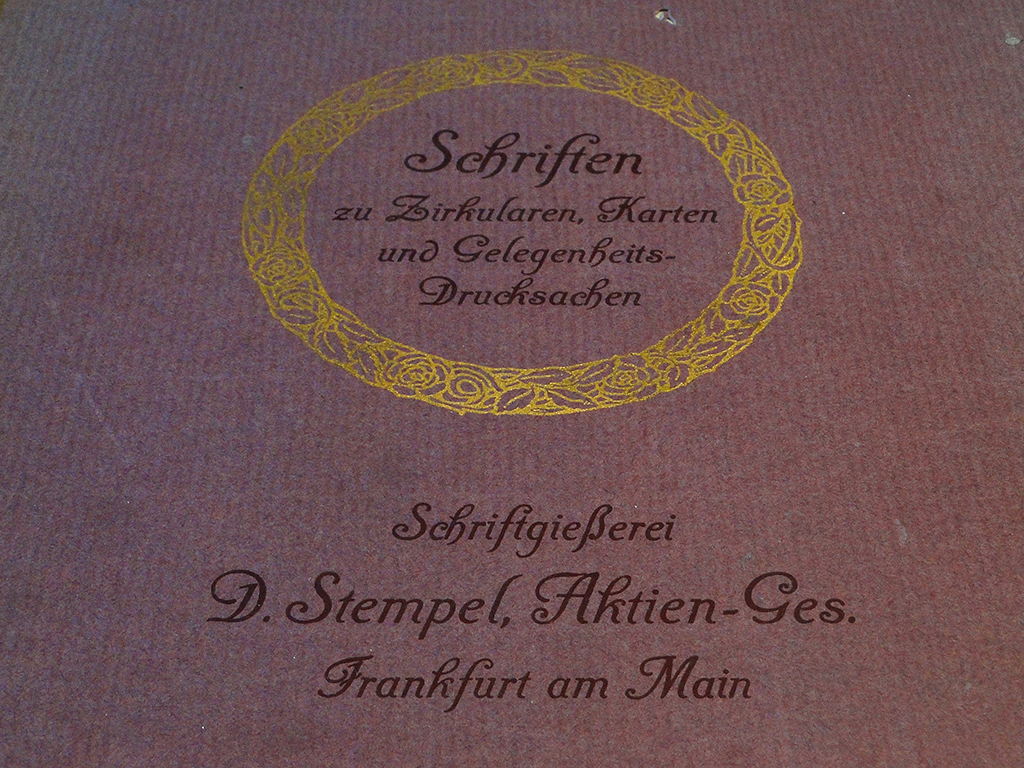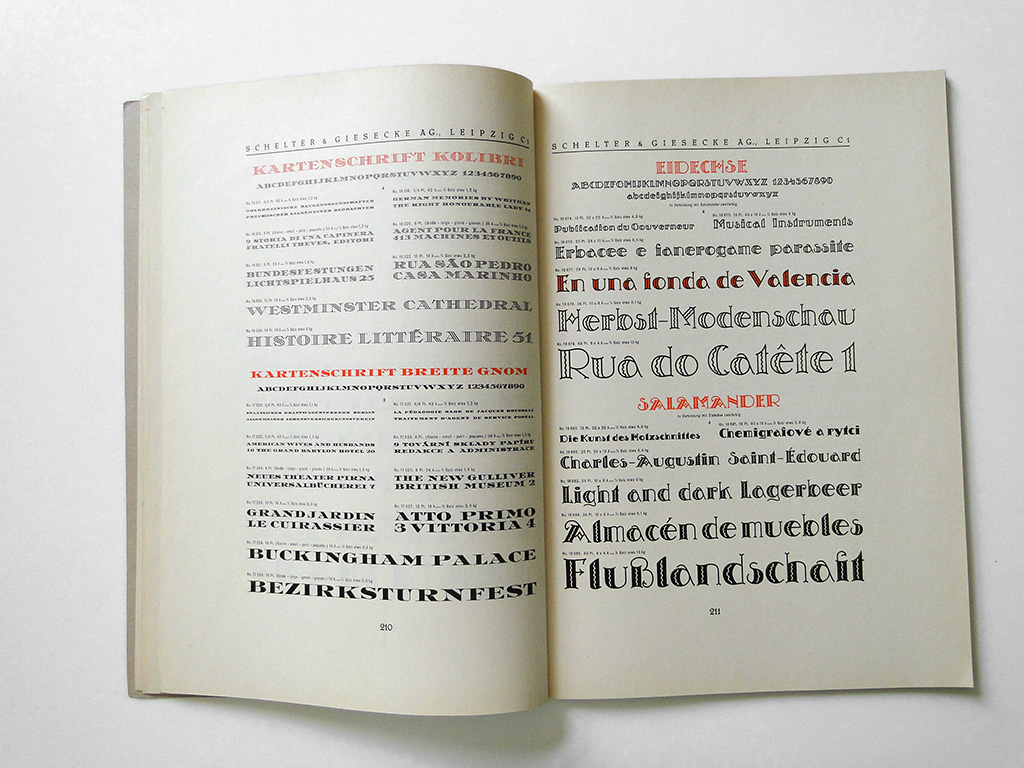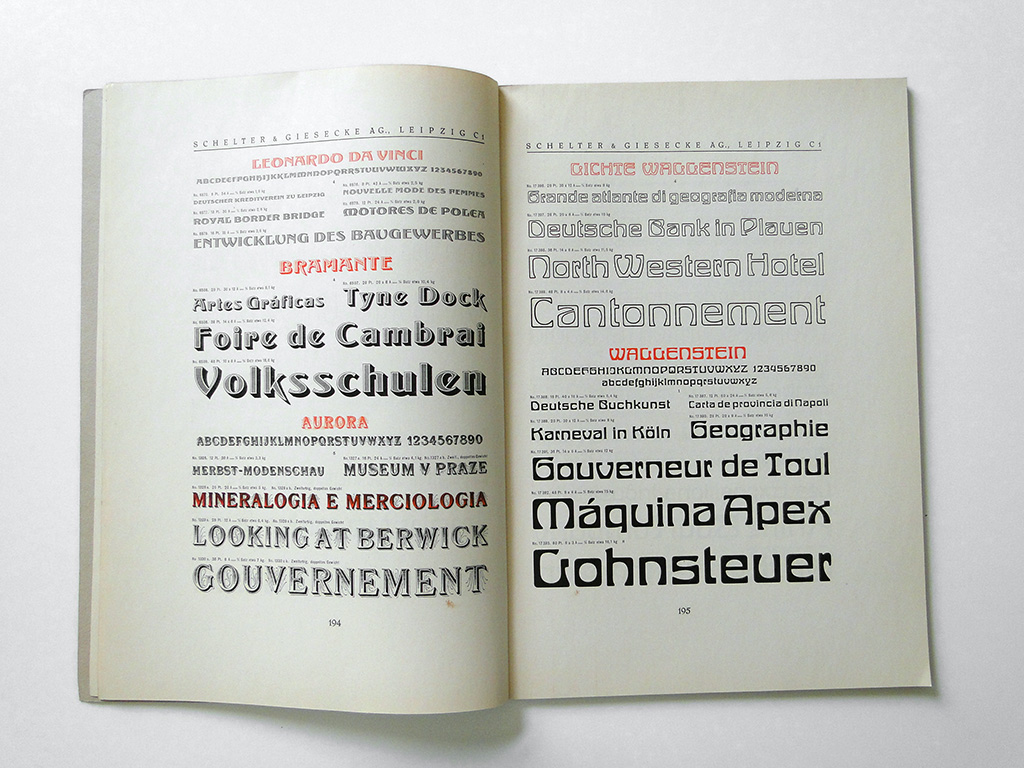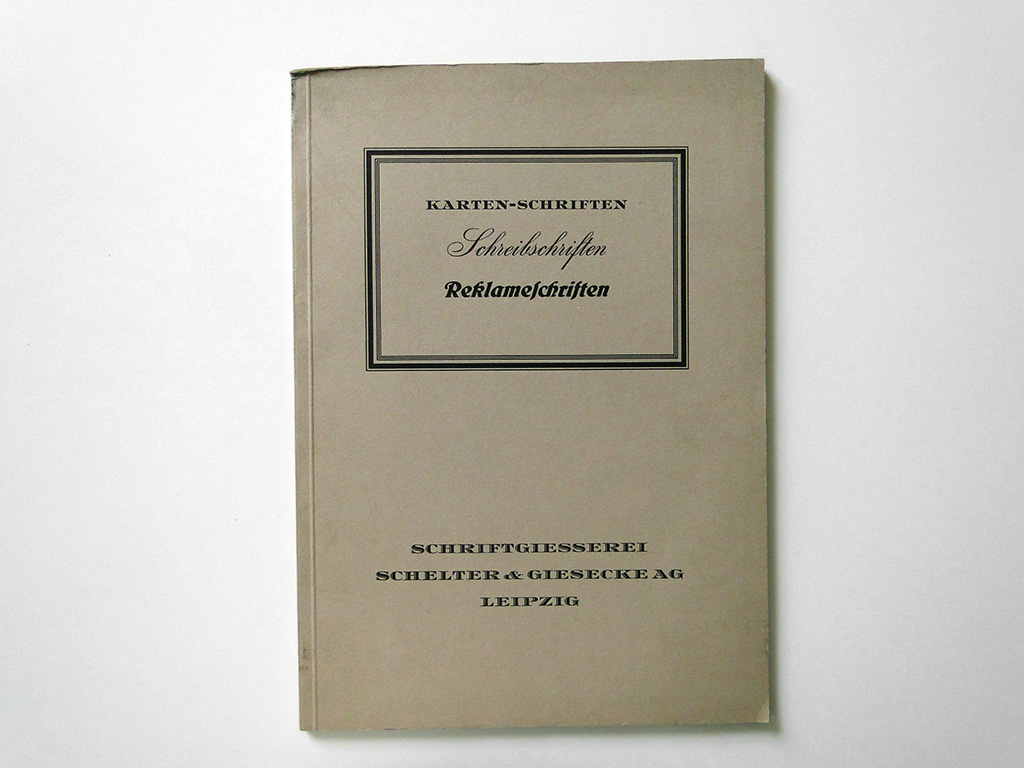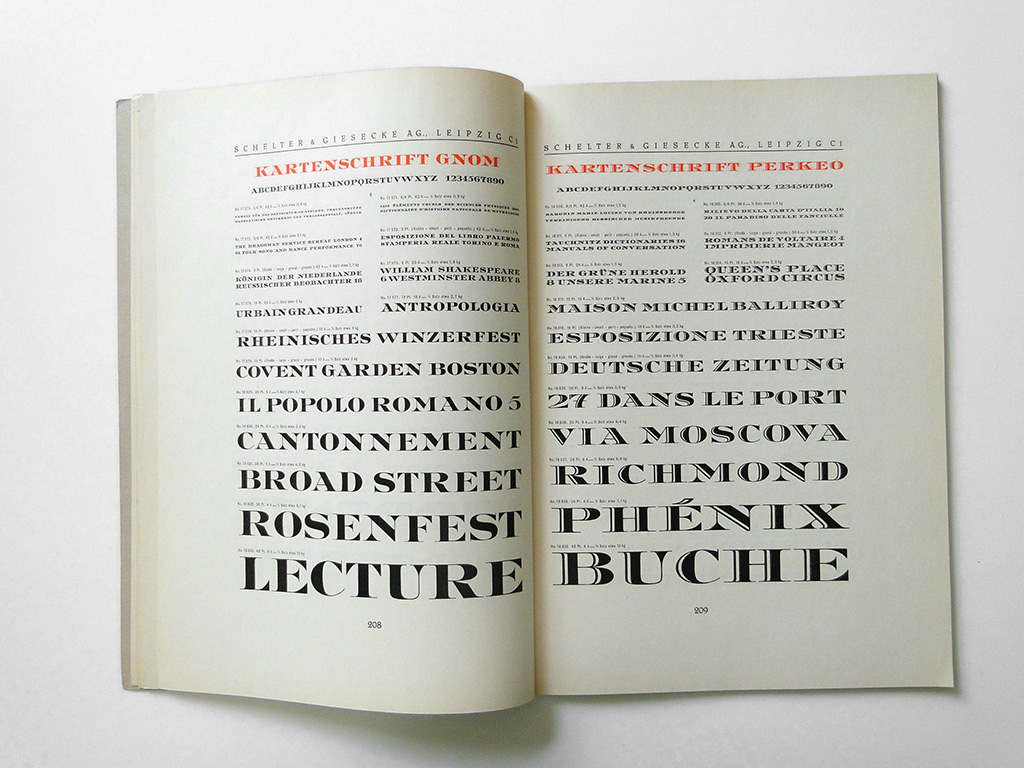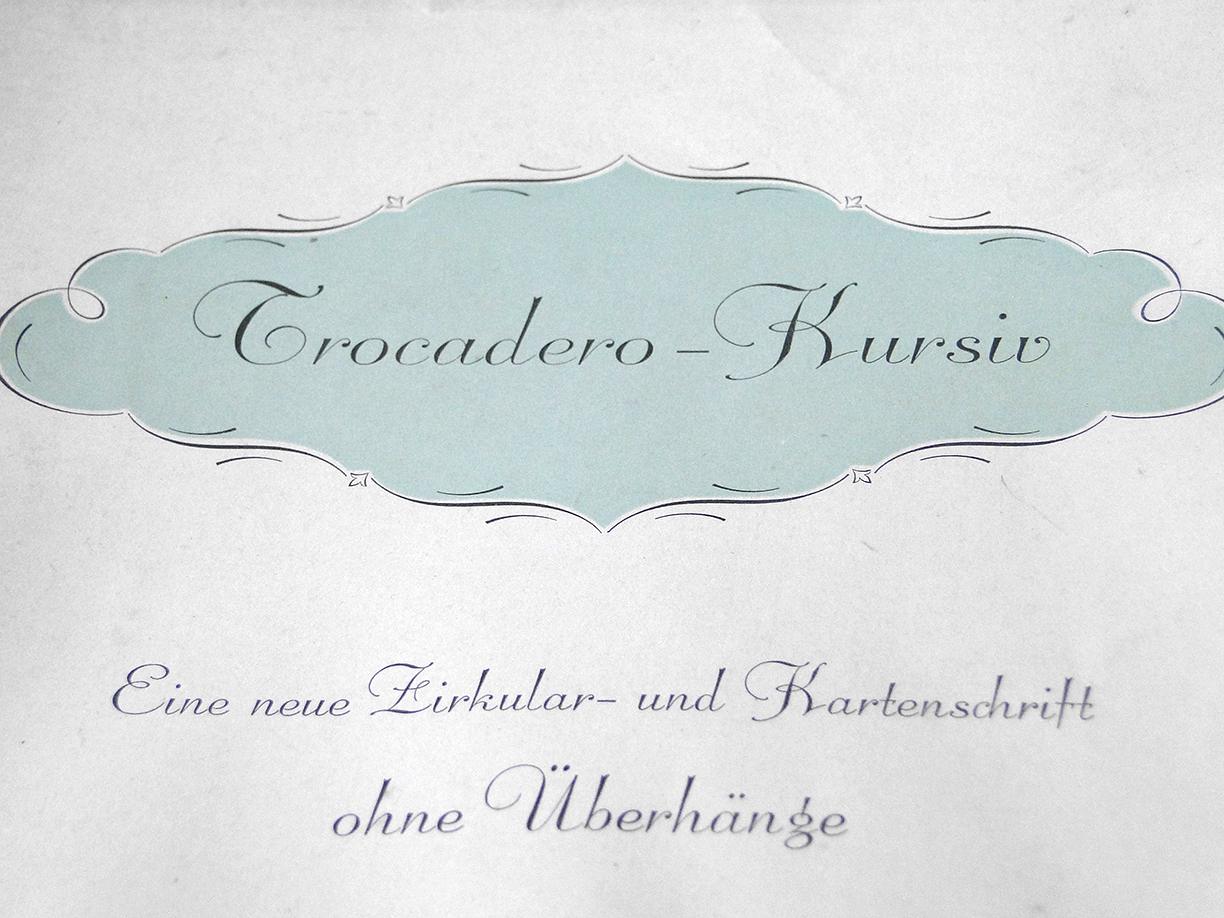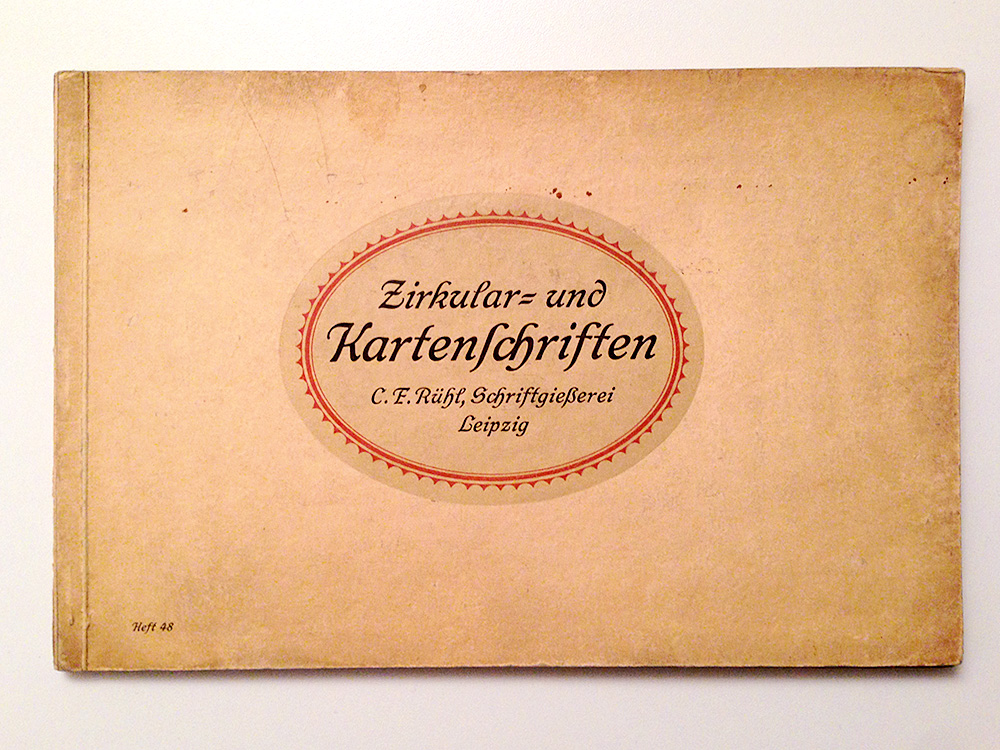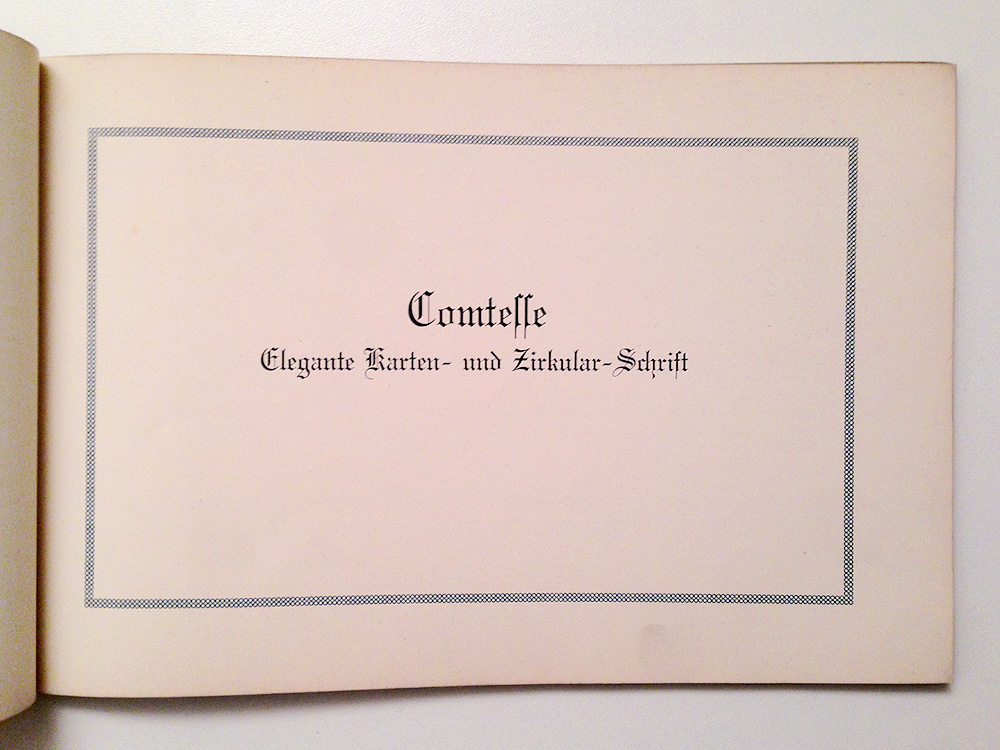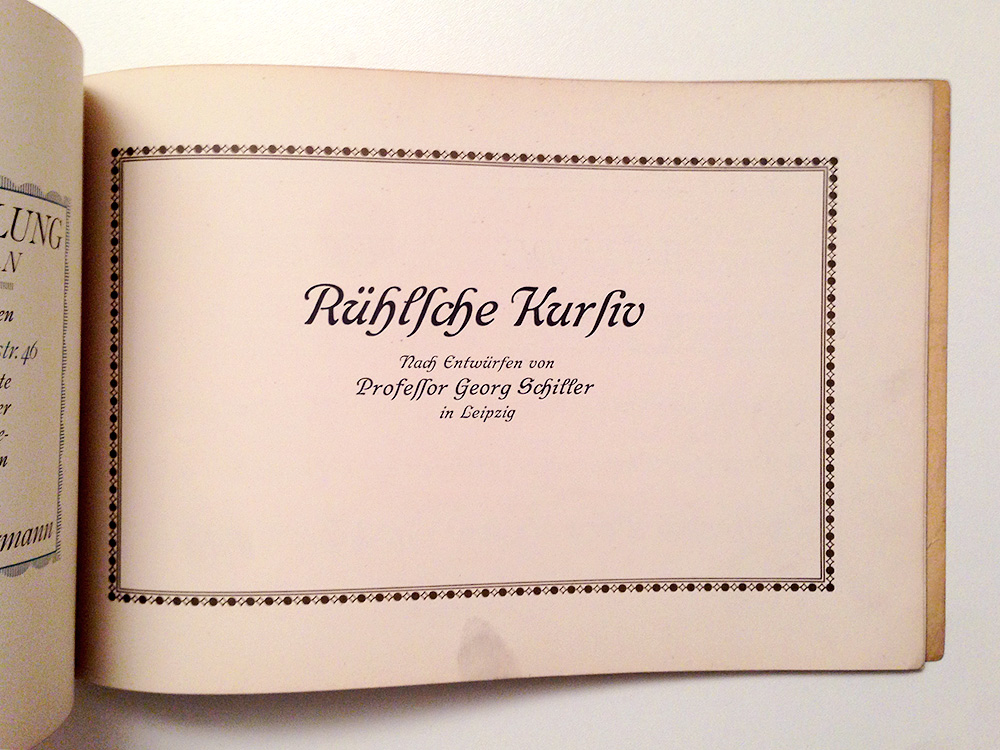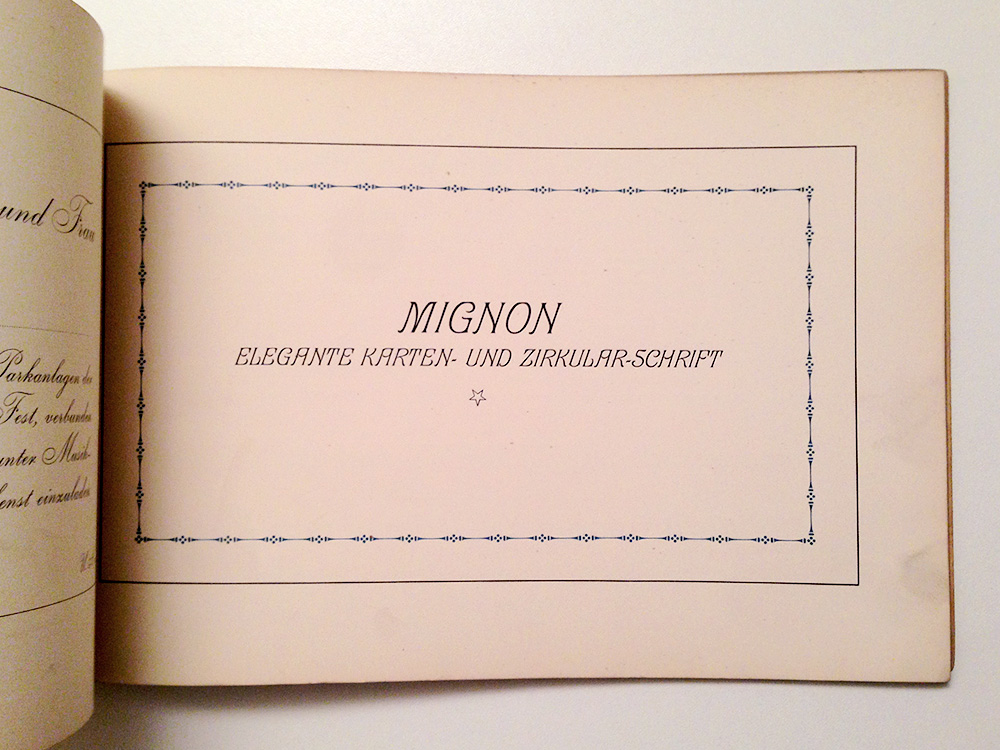
Definition Kartenschriften
Manche Bleisatzschriften werden als Kartenschriften kategorisiert oder tragen diese Bezeichnung sogar im Namen. Ich denke da immer zuerst an Landkarten, aber scheinbar bezog sich das ja früher eher auf Visitenkarten, Postkarten (?) und ähnliches.
Wie würde man »Kartenschriften« also definieren? Gibt es vielleicht sogar eine Quelle aus älterer Literatur dazu? Und was unterscheidet Kartenschriften dann vom Überbegriff(?) Akzidenzschriften?
Ich hab ein paar Muster mit Kartenschriften und kann mal schauen ob sich darin Informationen finden ...
Ohne mich jetzt auf Quellen zu berufen:
Kartenschriften weisen meist einen Kupferstich- bzw. Lithografie-Charakter auf. Dazu gehörten u. a. schraffierte Schriften, Schriften im klassizistischen Stil, Kanzlei-Gotisch, Schriften mit oft ausgeprägten Serifen und ähnliche Schriften. Diese gab es jeweils auch oft in schraffiertem Stil.
Nach Erfindung des Kupferstiches bzw. der Lithografie wurden alle möglichen Karten in diesen Druckverfahren hergestellt.
Mit den entsprechenden Schriften griff man nun im Bleisatz auf diesen Stil zurück um ähnliche Ergebnisse im Hochdruck zu erzielen und kostengünstiger zu produzieren.
Schriften dieser Art eigneten sich in erster Linie für Karten und weniger allgemein für Akzidenzen.
Es  werden auch heute noch in kleinen Spezial-Druckerein Karten gestochen und im Stich-Tiefdruck hergestellt.
Dazu in Richard L. Neil, Satztechnisches Taschenlexikon, Wien 1925:
„Karte ist eine abgekürzte Bezeichnung. Es kann damit eine Visit-, Adress-, Korrespondenz- oder Postkarte, Ansichtskarte-, Geschäfts-, Mitglieds-, Vermählungs-, Verlobungs- oder Eintrittskarte o. dgl. gemeint sein.“
Über "Karten" gibt es einen sehr guten Artikel im Jahrbuch des OÖ. Musealvereines. Hier nur ein kleiner Auszug aus dem Beitrag. (Quelle: Ingeborg Micko: Nimm mit Huld die kleine Gabe – Freundschafts- und Glückwunschkarten des Biedermeier im Stadtmuseum Wels. In: Festschrift für Walter Aspernig zum 70. Geburtstag, Jahrbuch des Oberösterreichischen Musealvereines – Gesellschaft für Landeskunde, 157. Band, Linz 2012 = 36. Jahrbuch des Musealvereines Wels, Wels 2009/2010/2011):
„… Die ersten Nachrichten über Glückwunsch- und Freundschaftskarten finden sich bereits 1779 in einer Anzeige im Wiener Diarium, worin „auserlesene ernst- und scherzhafte Neujahrswünsche“ angeboten wurden. Geschäftstüchtige Kunsthändler, allen voran Johann Hieronymus Löschenkohl, nahmen sich der neuen Mode an, die durch die aus Frankreich stammenden Visitbillets inspiriert waren. Seit der Mitte des 18. Jahrhunderts war es in Frankreich und hier zunächst in aristokratischen, wenig später auch in bürgerlichen Kreisen Sitte geworden, Höflichkeitsbesuche abzustatten. Dabei waren die ersten Karten, die als Visitenkarten oder „Billets de visite“ abgegeben wurden, Spielkarten mit geschriebenen oder gedruckten Namen. Daraus entwickelten sich die Besuchskarten, die den Namen des Inhabers trugen, umrahmt von einfachen Kartuschen bis hin zu bildlichen Szenen und Allegorien. Diese Mode fiel zusammen mit dem Aufkommen der in Frankreich erneuerten alten Sitte, zum neuen Jahr Glückwunschkarten auszutauschen. Bereits im 15. Jahrhundert verschenkte man Holzschnitte als Neujahrsbildchen, die bis zur Reformation stets mit dem Bild des Jesusknaben bedruckt waren. Die Verleger populärer Gebrauchsgrafik erkannten in diesem wiederbelebten Brauch einen vielversprechenden Markt und erweiterten ihr Warenangebot um spezielle Glückwunschbillets …“
„… Die in Frankreich zur großen Mode gewordenen Glückwunschkarten schlugen in Wien ein und setzten sich wie sonst nirgendwo durch. In der ersten Hälfte des 19. Jahrhunderts brachten mehr als 80 Verleger in Europa Glückwunschkarten heraus, davon 40 allein in Wien. Weitere Verlagsorte waren unter anderen Paris, Prag, Berlin, Nürnberg, Augsburg oder München. Zur Bedeutung Wiens als Produktionsort und Handelsplatz von Gebrauchsgrafik trugen Kaiserin Maria Theresia (1717–1780) 1766 mit der Gründung der k.k. Kupferstecher-Akademie und Kaiser Joseph II. (1741–1790) mit dem 1784 erlassenen Einfuhrverbot für bestimmte ausländische Waren und der teilweisen Aufhebung des Zunftzwangs bei …“
Ralf, mir ging es auch jahrelang so, dass ich immer zuerst an Landkarten gedacht habe, aber irgendwann belehrte mich ein älterer Kollege in dem Sinn, wie Herr Krump das so schön beschreibt. Ein Indiz, dass Kartenschriften nicht als Landkartenschriften zu verstehen waren, ist vielleicht, das unter dem Begriff "Kartenschrift" nach meinem Kenntnisstand niemals linkskursive Schriften verzeichnet worden sind, die ja nun eindeutig und eigentlich ausschließlich für Landkarten geschaffen waren.
Das linke Muster von Emil Gursch war eines meiner ersten Schriftmuster in meiner Sammlung bis dahin dachte ich auch immer es handelt sich bei Kartenschriften um Landkartenschriften. Hier noch ein kleiner Nachschlag.
Wurden Landkarten denn jemals mit Bleisatzschriften bedruckt? Waren die Schriftzüge nicht immer in die Vorlagen eingeschrieben? Ich habe noch keinen Bleisatz für Landkarten gesehen.
Der Begriff der Kartenschrift umfaßt irgendwann alle Arten von Schriften, die nicht für Werksatz verwendet wurden, es war ein reiner Reklame-Begriff. Man sieht das an den Mustern aus der Gießerei Gursch. Ich habe eine häßliche Serifenlose in Blei namens Kartenschrift Fedora. Noch nie eingesetzt.
Hatten wir nicht schon vor gar nicht so langer Zeit die kartografischen Schriften, wie Römisch Venus und Kursivschrift, wie auch den kartografischen Bleisatz, der Typometrie am Wickel?
Der Begriff Kartenschrift ist reine Marketingsprache, mehr steckt nicht dahinter. Oft waren es ornamentale, schattierte und Schnörkelschriften, die dem Drucker schmackhaft gemacht werden sollten. Natürlich kann man ebenso gute und wahrscheinlich bessere Akzidenzen setzen mit Schriften, die nicht als Kartenschriften beworben wurden, also den Klassikern. Garamond, Caslon, Didot usw. wurden nicht als Kartenschriften beworben. Aber eben durchaus auch Serifenlose, die der Vertreter der Gießerei dem Drucker verkaufen wollte. Weil sie etwas anders (meistens schlechter) als die gebräuchlichen waren, erzählte man dem Drucker, sie seien für Akzidenzen (das waren vor allem Karten für etliche Anlässe) besser geeignet als die Ware, die er im Kasten liegen hatte und die der Gießerei kein Geld mehr einbrachte.